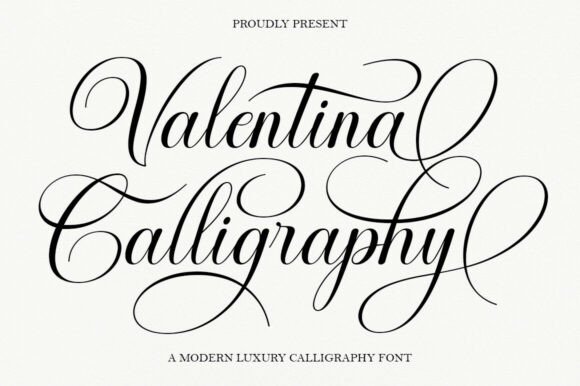
Valentina Calligraphy
Qu’est‑ce que Valentina Calligraphy ?
Valentina Calligraphy est une police de caractères script de style « copperplate » revisité pour les designers contemporains. Elle combine la grâce intemporelle de la calligraphie décorative avec un raffinement moderne, créant une écriture fluide, élégante et parfaitement lisible.
Points forts de la fonte
- Design soigné : chaque boucle, chaque empattement est finement détaillé pour une allure sophistiquée.
- Lisibilité : lignes claires et espacées garantissent une lecture sans effort, même en petits formats.
- Variété de ligatures et d’alternatives : plus de 30 combinaisons de lettres et d’ornements pour un style unique.
- Compatibilité PUA : accès facile aux alternatifs sans nécessiter de logiciels de dessin avancés.
- Polyvalence : idéale pour les invitations, logos, menus, emballages beauté, couvertures de livres, magazines et publicités.
Applications créatives
Que vous soyez graphiste, wedding planner ou responsable marketing, Valentina Calligraphy s’adapte à vos projets :
- Invitations de mariage avec une touche de luxe
- Branding de marques de haute couture ou de produits de beauté
- Menus de restaurants gastronomiques
- Cartes de vœux et papeterie de luxe
- Couvertures de livres, magazines et publicités haut de gamme
Pourquoi choisir Valentina Calligraphy ?
Avec sa combinaison d’élégance classique et de touche contemporaine, Valentina Calligraphy transforme vos projets en œuvres raffinées. Sa lisibilité, sa variété d’alternatives et sa compatibilité font d’elle un indispensable pour tout designer recherchant une solution typographique haut de gamme.
Conclusion
Valentina Calligraphy est bien plus qu’une simple police : c’est un outil de création qui apporte sophistication, féminité et modernité à chaque texte. Son style unique et sa facilité d’usage en font le choix privilégié pour les projets haut de gamme, des invitations de mariage aux marques de luxe.